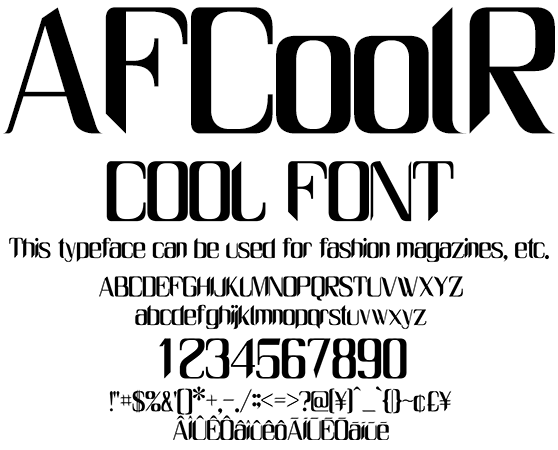
お洒落系欧文 AFCoolR
AFCoolR
お洒落でクールな欧文フォント、ファッション系のテキストに最適なレギュラーウエイトフォントです。ファッション系ドキュメント、動画テロップ、WebPage にご利用ください。日本のローマ字表記で使われる訓令式やヘボン式で扱う Ô や Ō を収録、人名地名へのアプローチもリアルです。